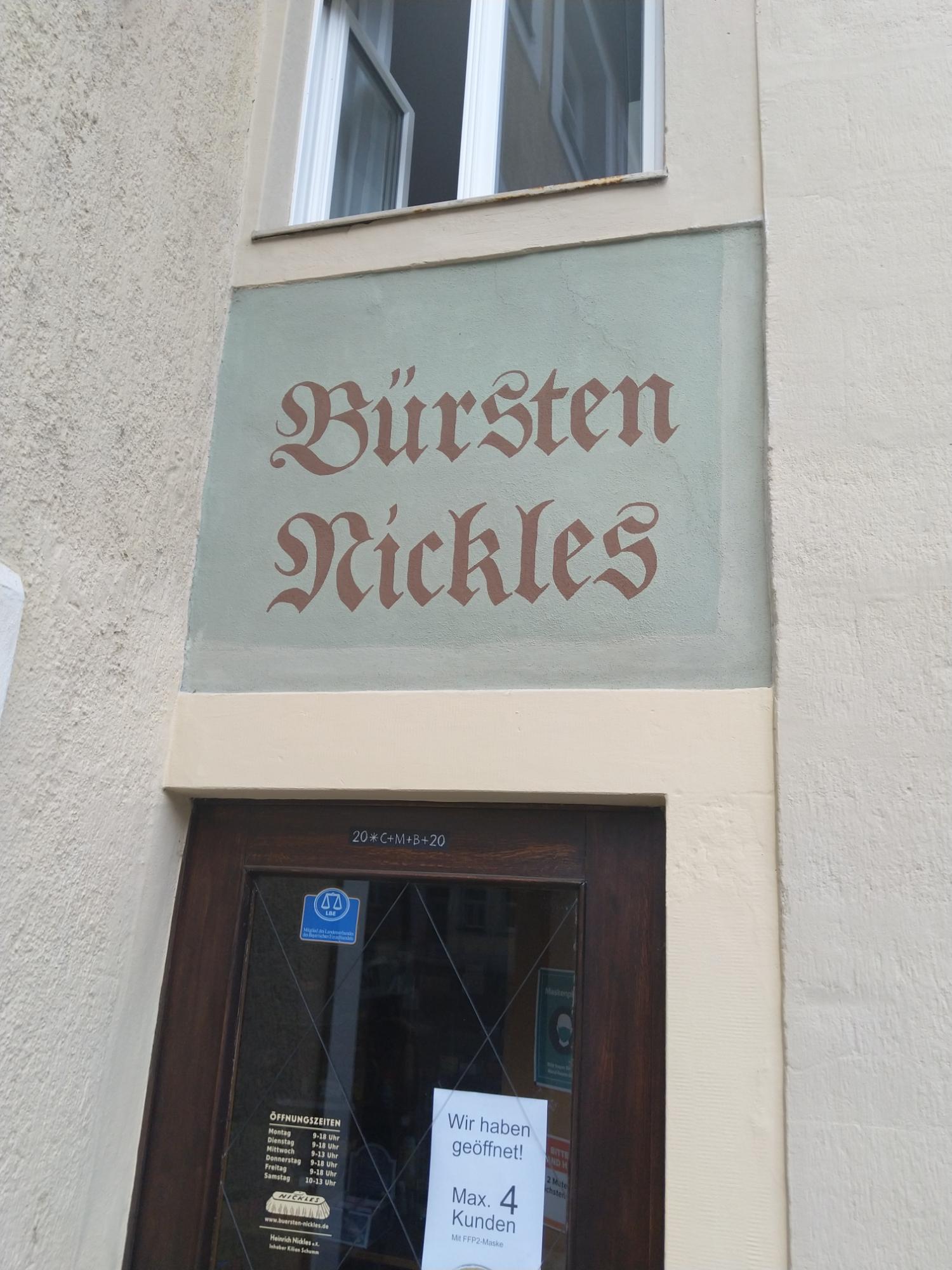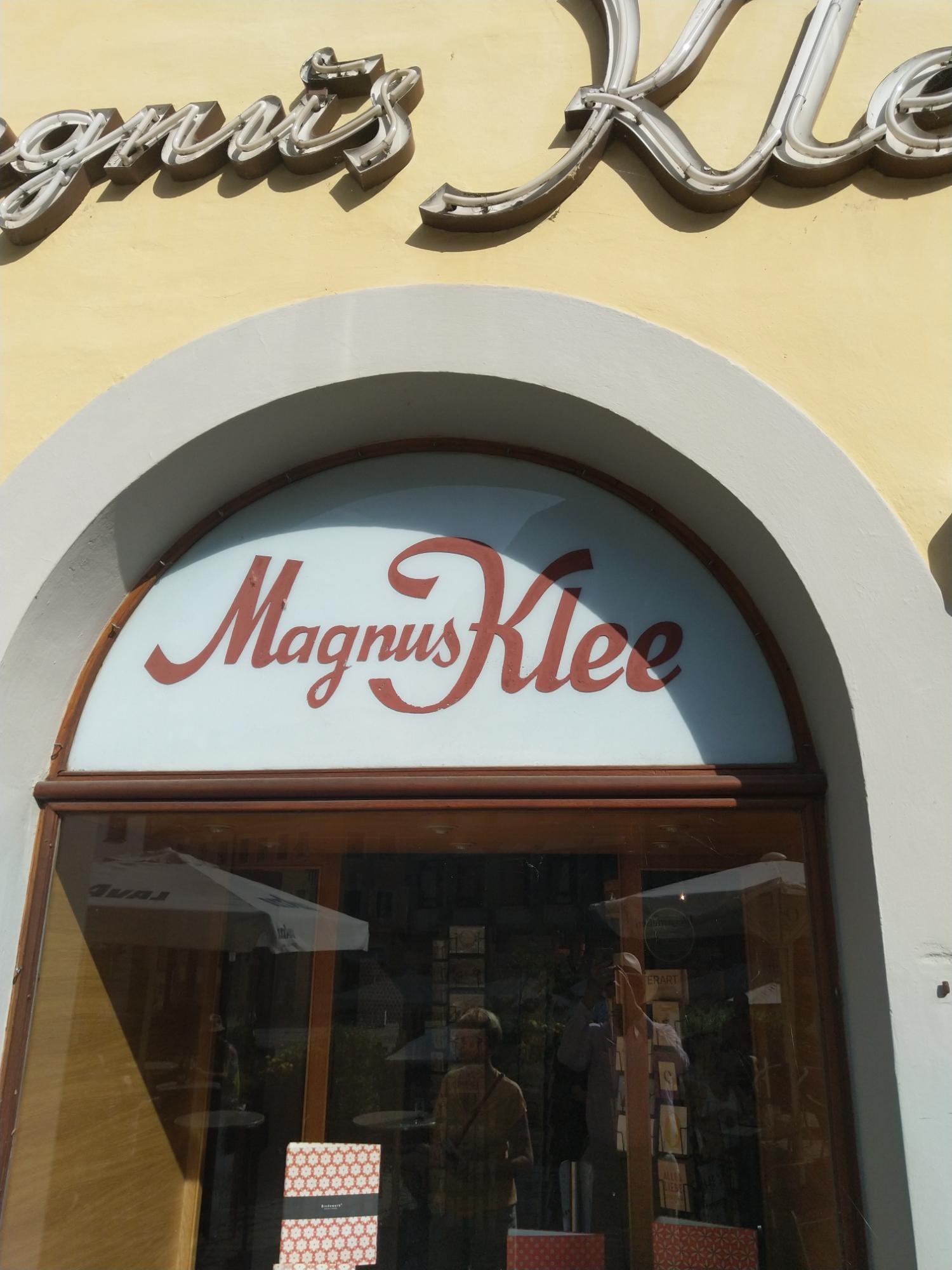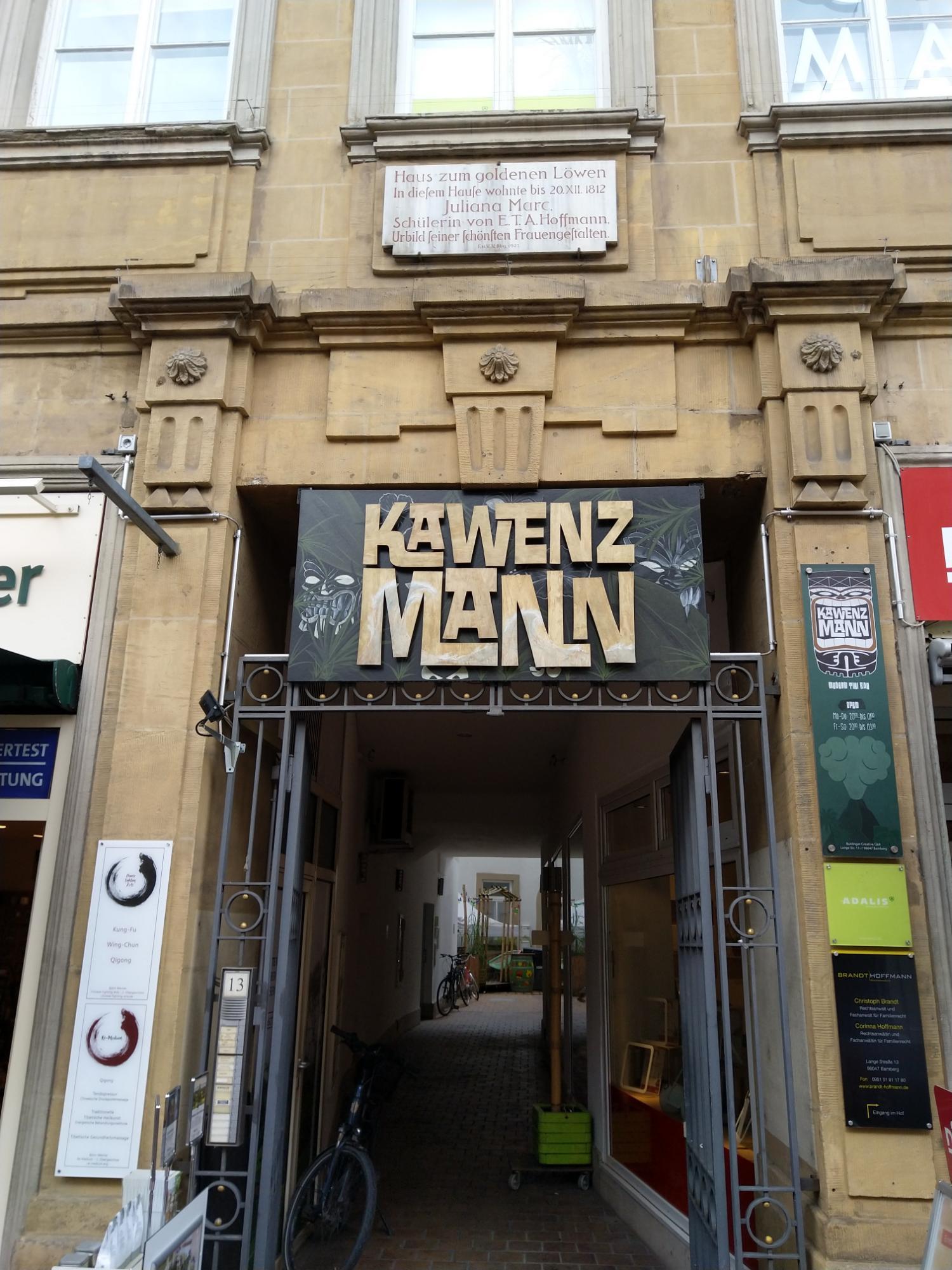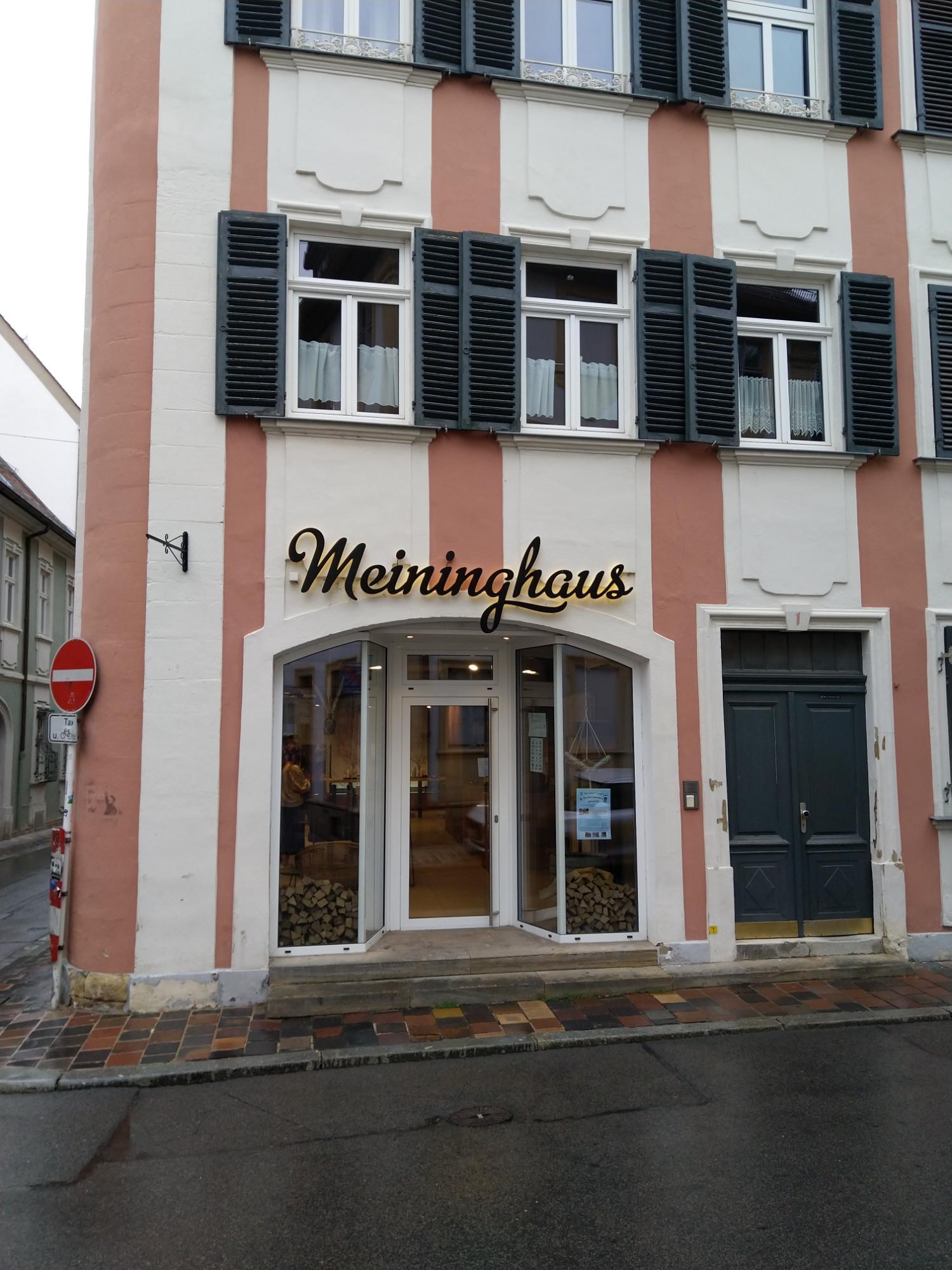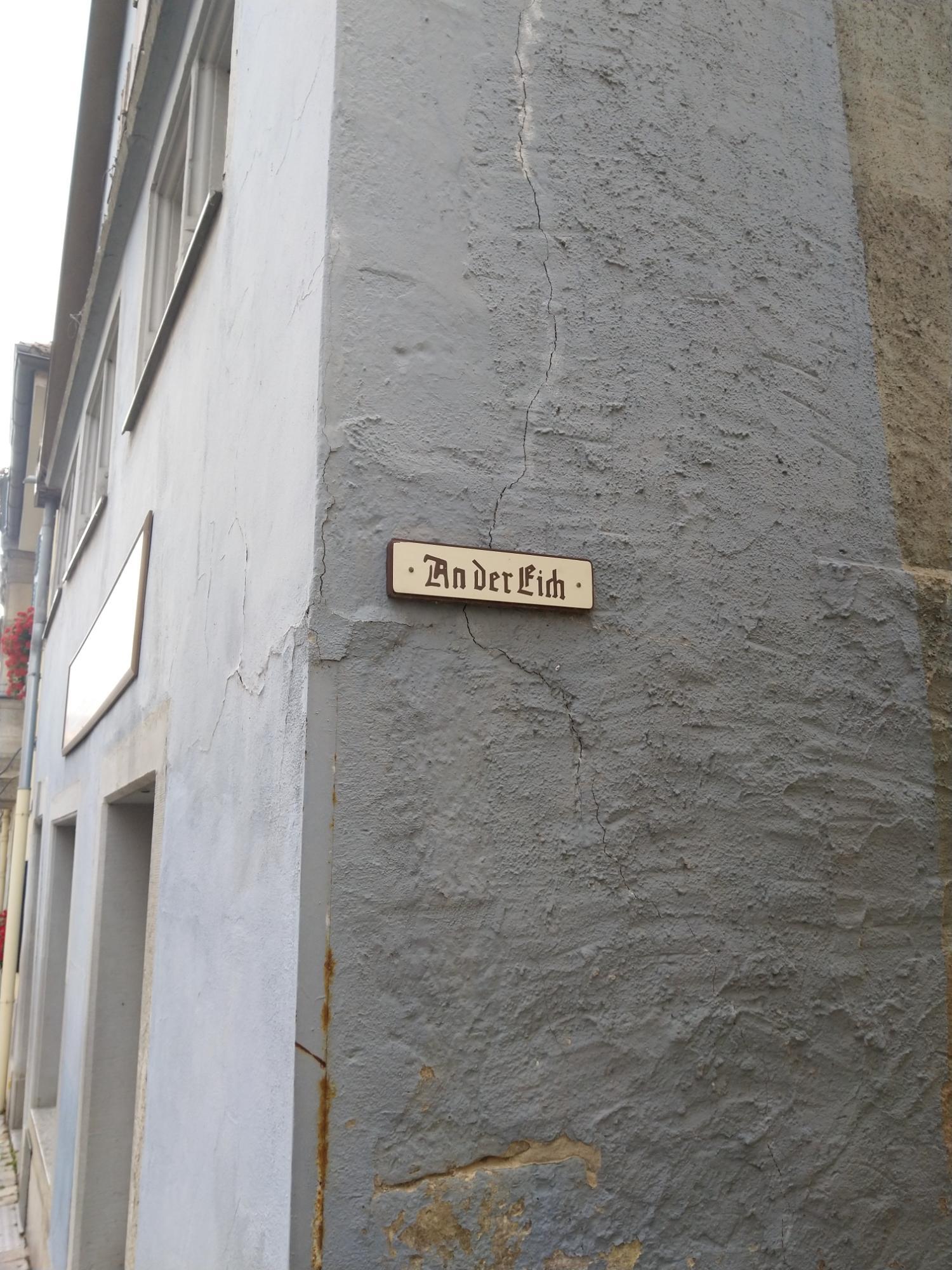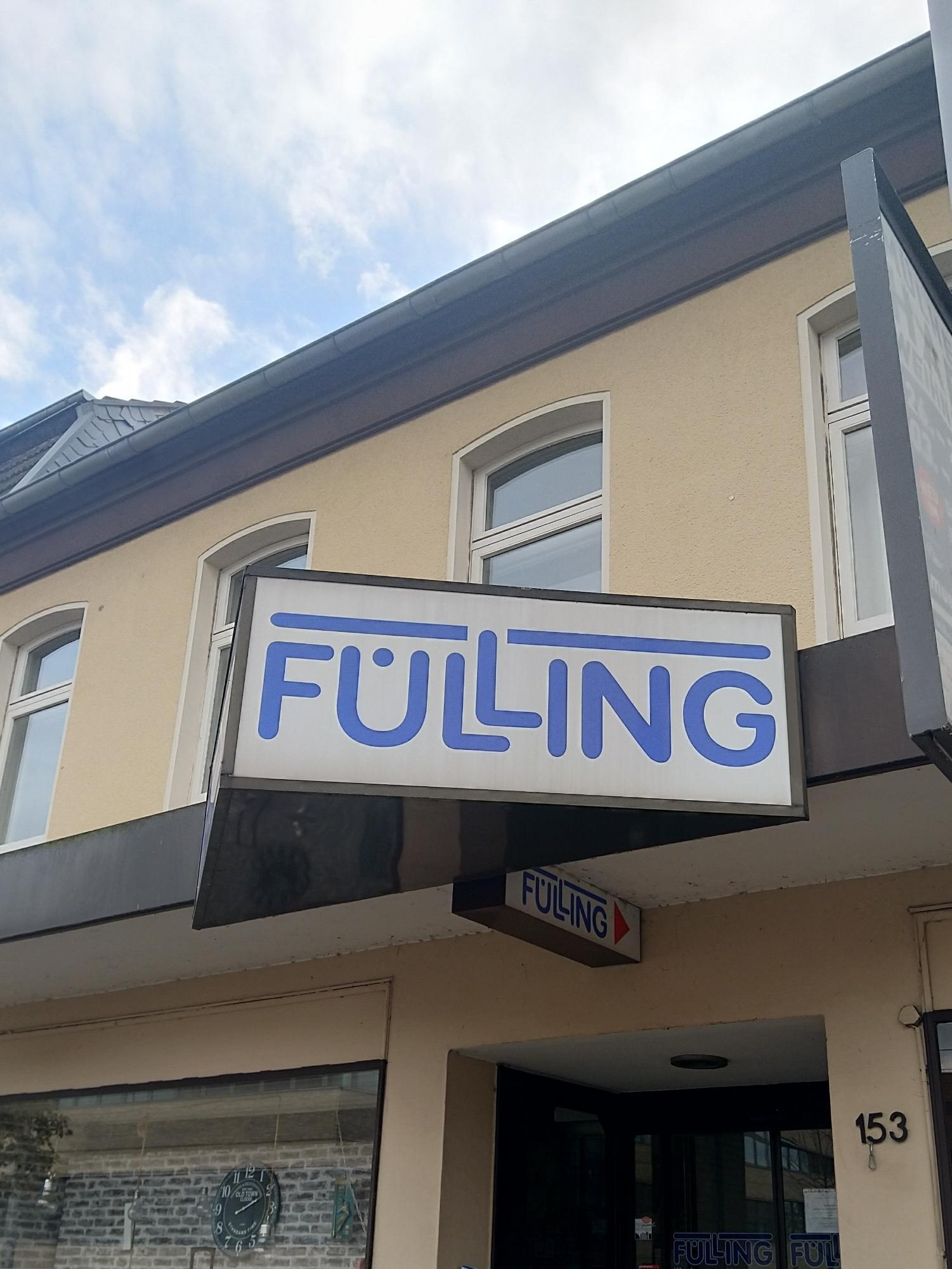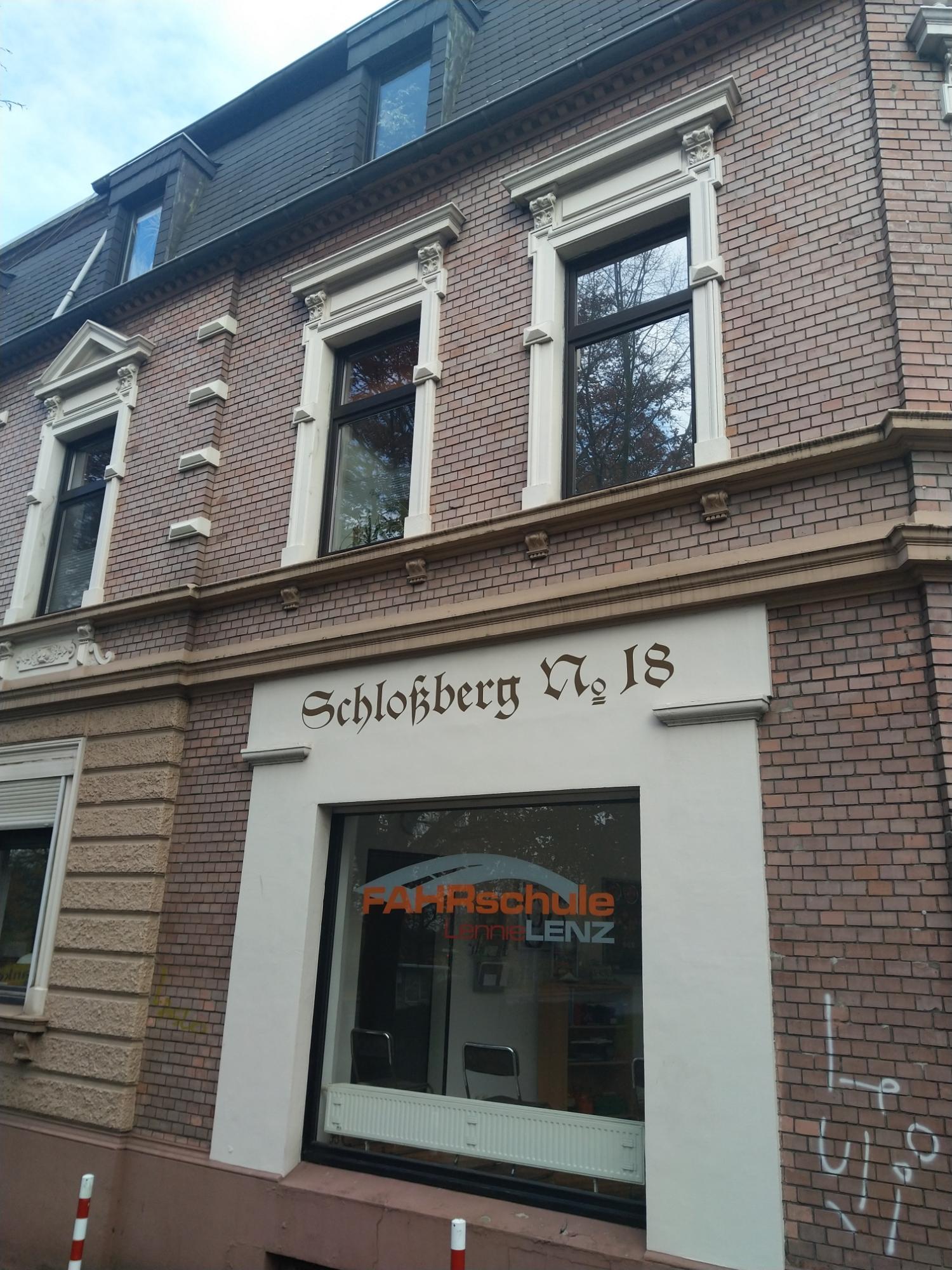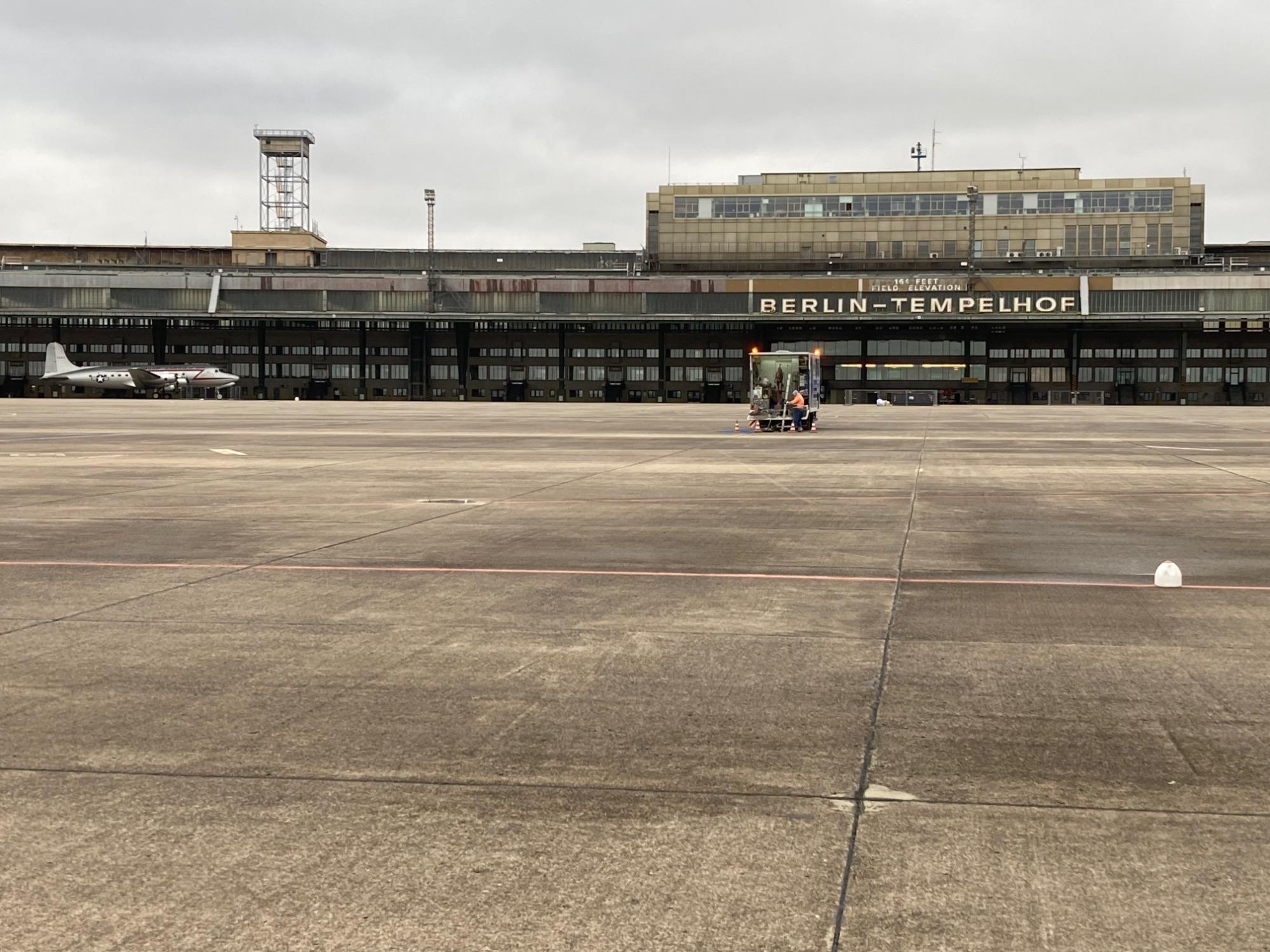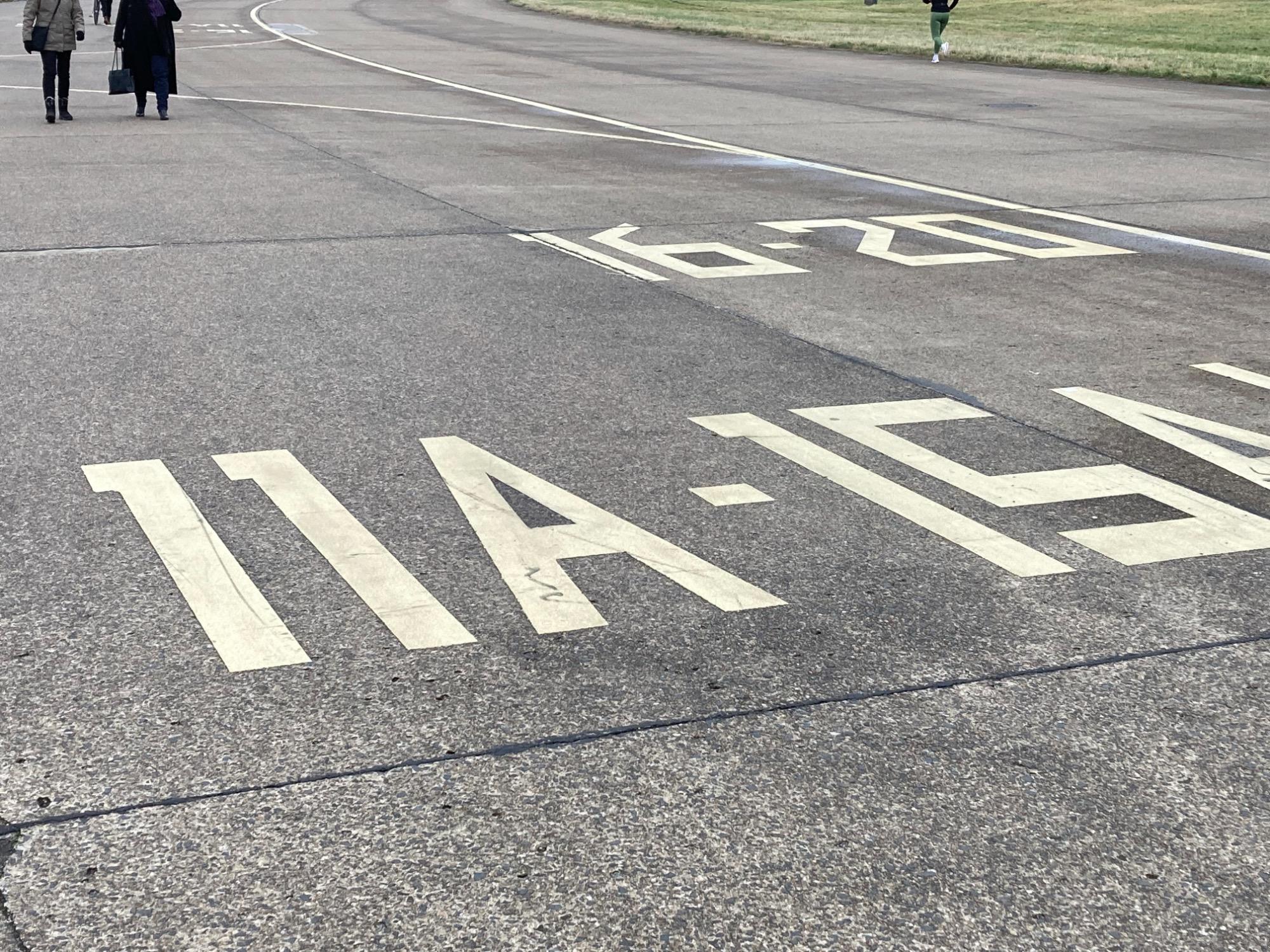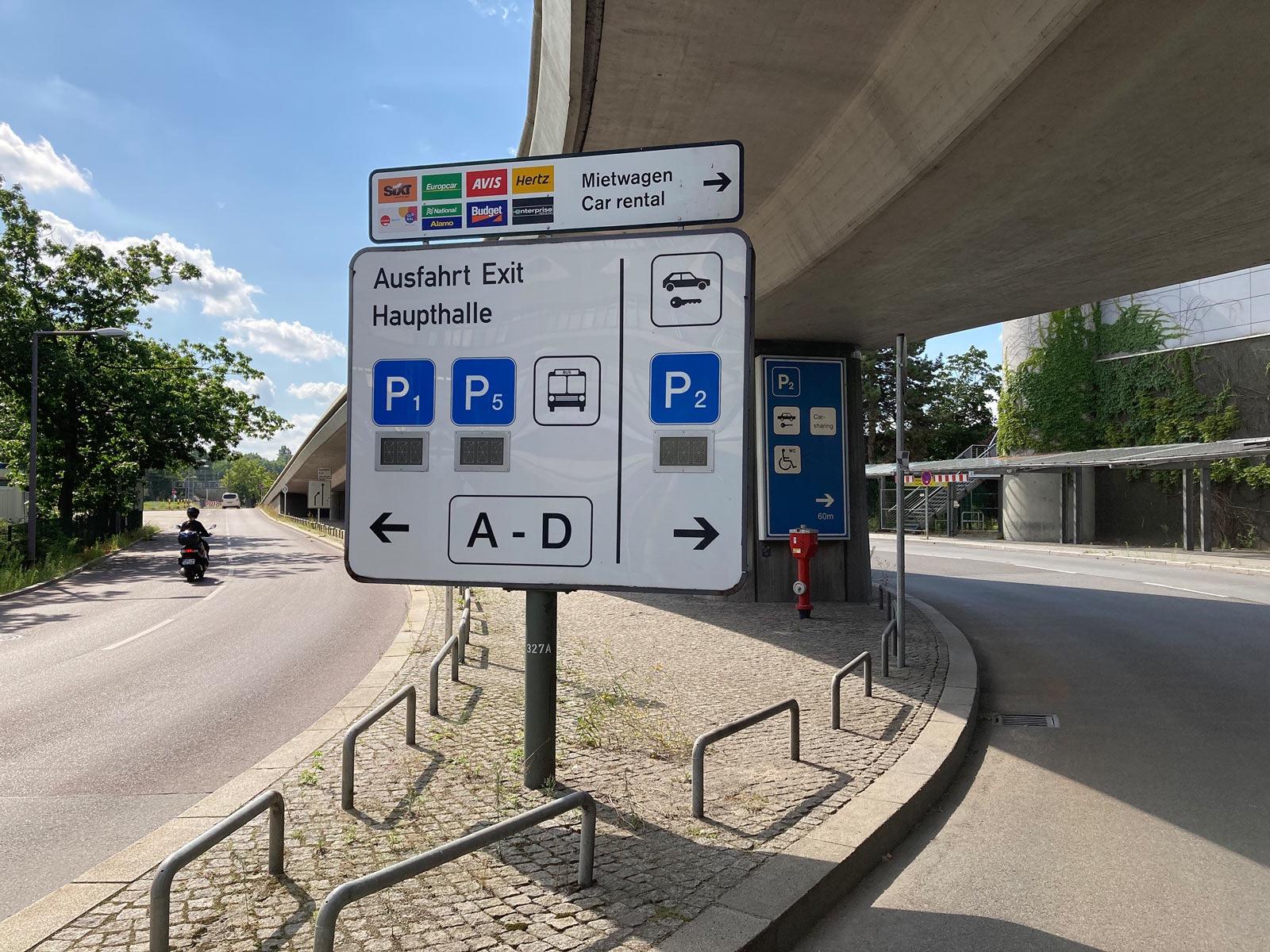
Typostreifzug durch die Stadt ...
catfonts wird sicher einen Knochen- oder Palmen-Font daraus kreieren :lol:.
Ein Grabstein im Nachbarort. Dieser Schiefer ist sehr hart und beständig. Ich dachte mir, Hut ab vor dem Steinmetz der hier so viel Schriftkunst zeigt. Besonders die Ziffern gefielen mir sehr.
Dann erst ging mir auf, daß hier sechs Geschwister in nur zwei Wochen starben.  In den 1770ern wurde Boston und Umgegend von verschiedenen Epidemien heimgesucht. Die Todesursache hier ist anscheinend nicht bekannt, wird aber wohl Diphtherie, Ruhr, o. ä. gewesen sein. So einen Stein möchte ich jedem Antivaxxer vor die Tür stellen.
Beim Kawenzmann-Schriftzug handelt es sich um einen Font, die Ed Interlock.
sehr schön! ich liebe ja schriften mit eingebauten (ot-)ligaturen. was ich mich schon länger frage: gibt es eine feine möglichkeit, die eigene schriftdatenbank auf diese eigenschaft zu durchsuchen? ich hab schnell mal in FEX was probiert, das ist mir (vorerst) aber zu unübersichtlich. bin wahrscheinlich grad betriebsblind.
andere idee: wir machen bei den fontlisten hier eine eigene mit dem gemeinsamen merkmal »superfeine ligaturen« (oder so)
Welcher Font? *d&r* ;-)
Habe außer der Überschrift noch nicht versucht, das zu entziffern ...
Im übrigen wird's bald abgerissen, ehemaliges Gelände der Amerikaner in der Karlsruher Nordstadt, dann vielfältig zwischengenutzt, hier KSC-Fanprojekt, demnächst Wohngebiet.
Chamissoplatz und Umgebung, Kreuzberg ca. 1978 im damaligen Westberlin, von Kleinbild-Negativen – die Fotos müssen wohl auf einem Ausflug entstanden sein, ich bin in Berlin-Schmargendorf aufgewachsen.
… in virus times, ahem (gar so schlimm steht es nicht um die Berliner Kinolandschaft, scheint ein spezieller Fall zu sein. Kann mich noch an die Zeit erinnern, wo es da Borsalino & Co. zur Matinee gab)
Seitdem das Junge Schauspielhaus in die ehemalige Fabrik (ich glaube, der Teil gehörte auch zu Heidenreich & Harbeck) am Wiesendamm eingezogen ist, komm ich immer wieder am Foyer vorbei und frage mich jedes Mal auf's Neue, ob es ein Versal-Eszett ist oder nicht. Durch mehrere Glasscheiben hätte es eines sein können, aber jetzt bin mir sehr unsicher. Vermutlich der Beleuchtung geschuldet ist das kränkelnde Gelb, in realiter sind die Glyphen gülden.
frage mich jedes Mal auf's Neue, ob es ein Versal-Eszett ist oder nicht.
Die Schrift ist ein reines Versalalphabet. Der Designer hat es also wohl für diese Anwendung gemeint. Gekonnt wirkt das aber nicht. Lustigerweise gehen andere Eszett-Formen des gleichen Designers, die ein Kleinbuchstabe sind, dann wieder eher als Großbuchstabe durch.